新装復刻版 変体英文字図案集
ビジュアル文庫「描き文字図案集」復刻シリーズ第3弾として、「新装復刻版 変体英文字図案集」が2018年8月30日に発売された。
1962年に佳生書房刊から刊行された「変体英文字図案集」を完全収録し、再構成した「描き文字図案集」復刻シリーズ。
第一章では、戦後の印刷物や看板などに書かれたアルファベット・英数字の字体から装飾などの様々な「英字スタイル」70パターンを掲載。
第二章では、ABCと数字をあらゆる角度から組み合わせた「英字モノグラム」約1,000種を収録している。
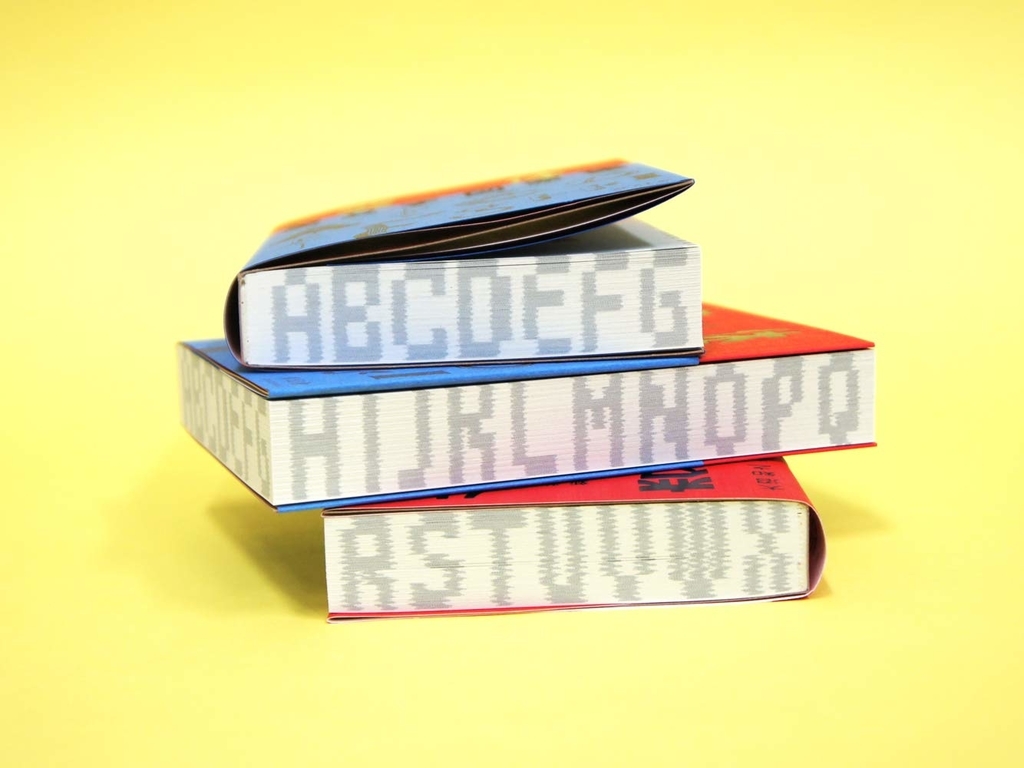
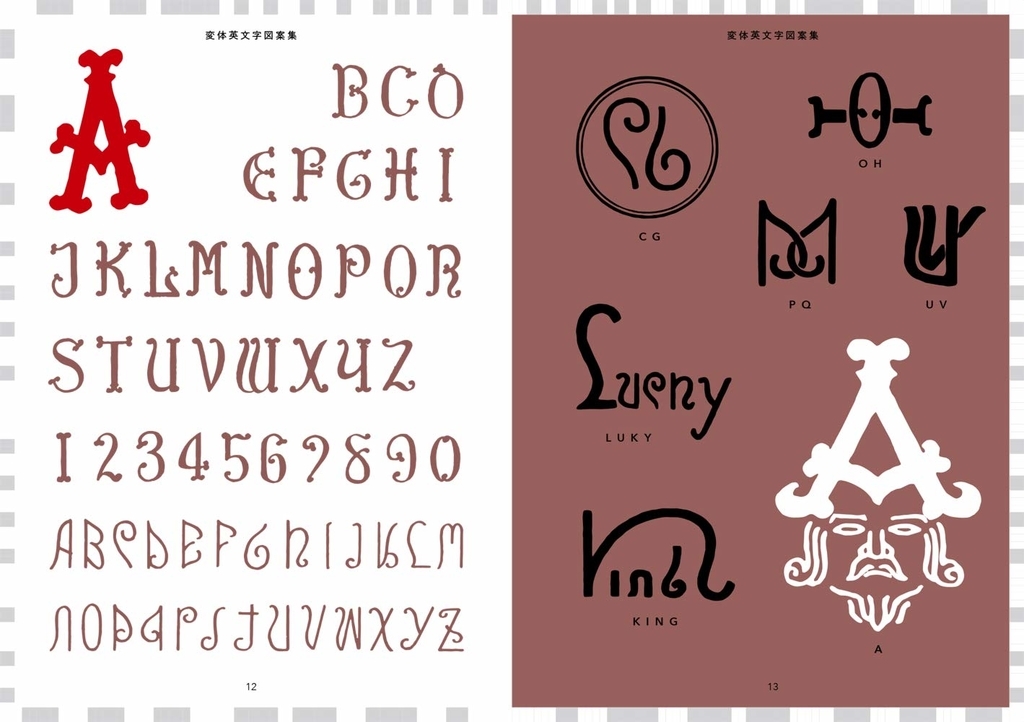
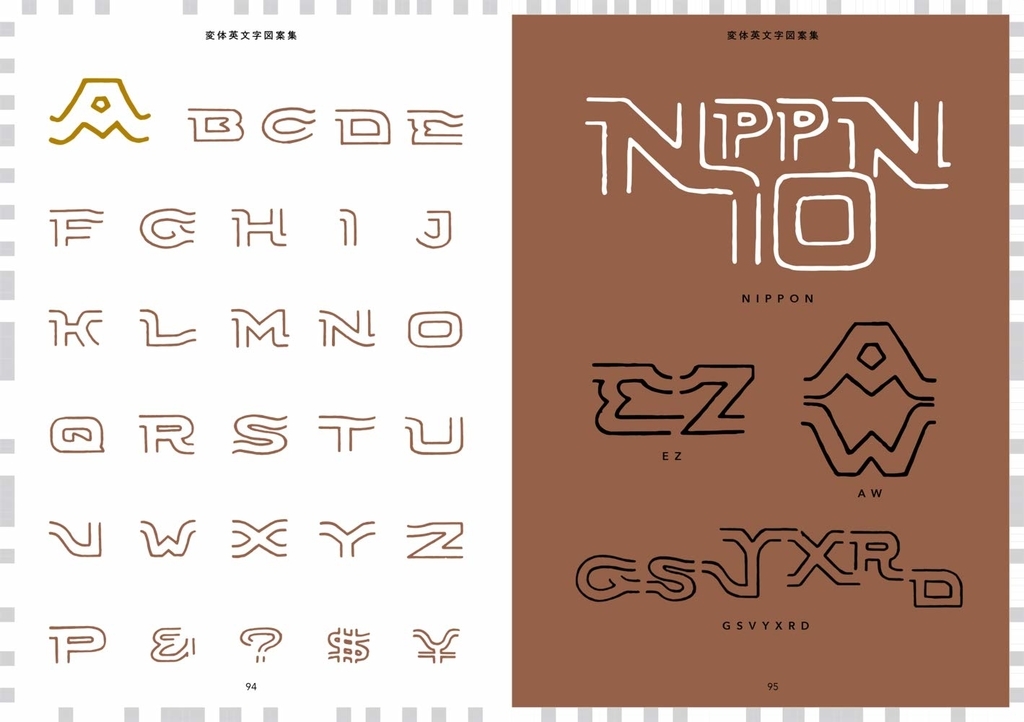
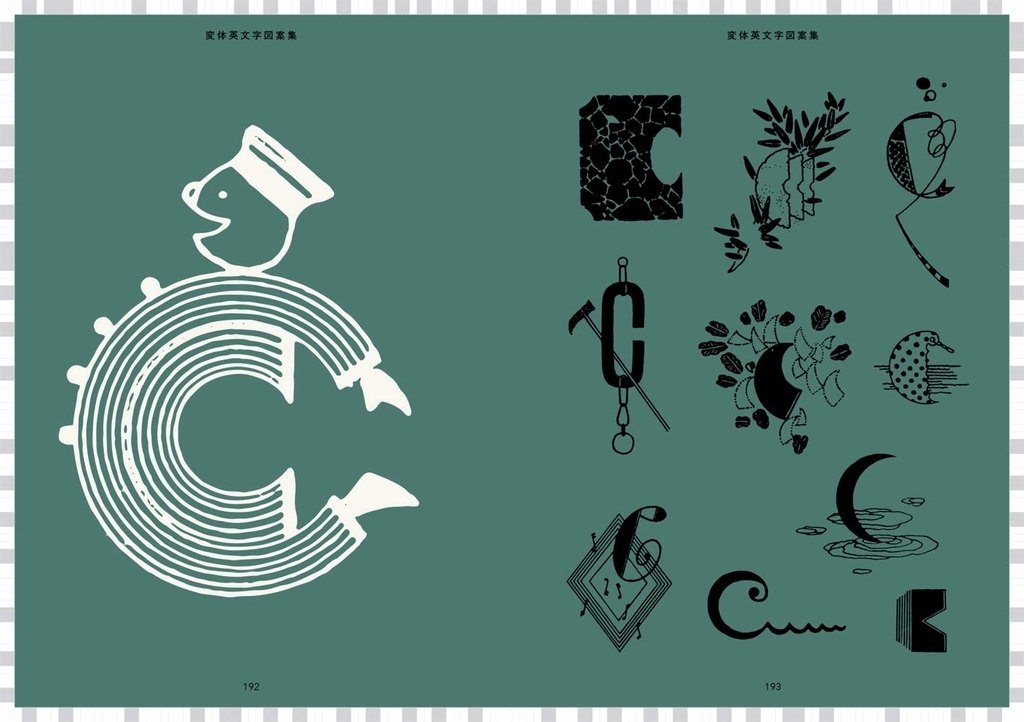
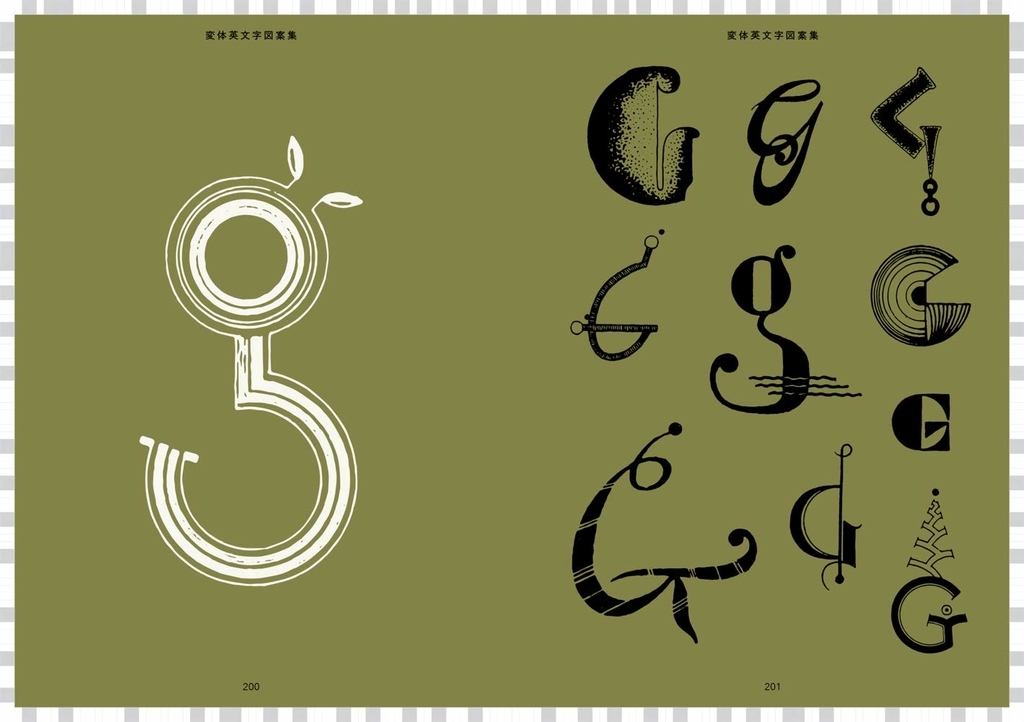
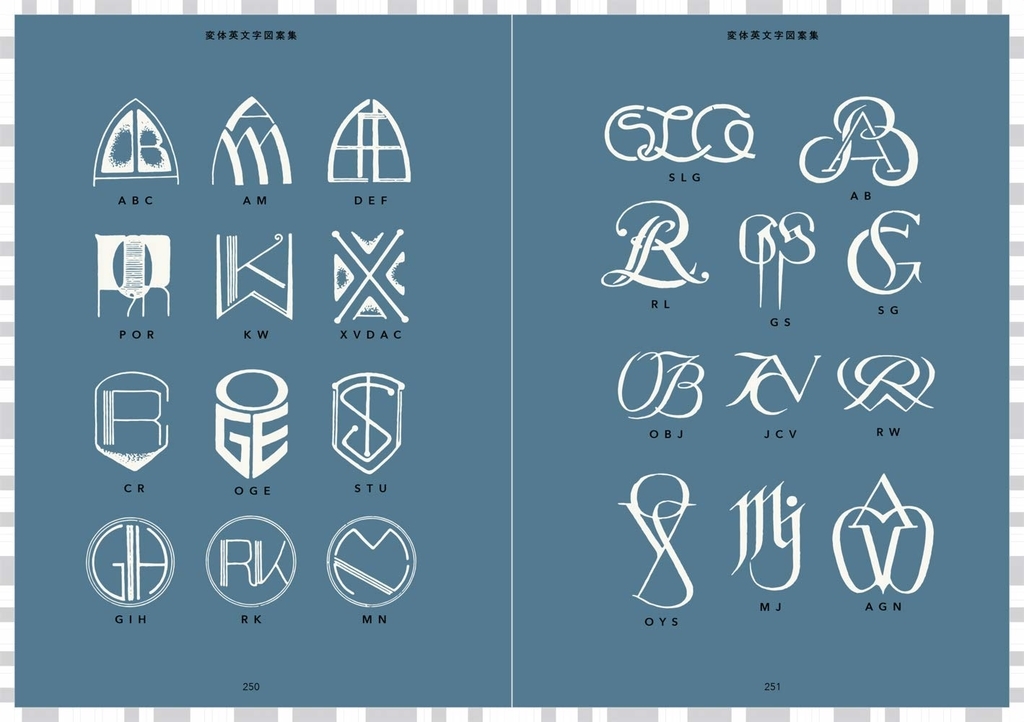
ビジュアル文庫 「描き文字図案集」復刻シリーズ 第3弾!
60年代、デザインの黎明期代に考案された楽しく、美しい英字の世界。
戦後の印刷物、掲示、看板などに書かれたアルファベットおよび英数字の実用的な字体をはじめ、装飾・美術的なさまざまなスタイルを第1章「英字スタイル」とし70パターン掲載。
これをもとに第2章「英字モノグラム」は、ABCと数字をあらゆる角度から組み合わせたモノグラムのバリエーションを約1,000種収録。
本書は、『変体英文字図案集』(1962年 佳生書房刊)を完全収録し再構成したものです。
序文 装丁家 平野甲賀
Title: Old-Style Alphabet Lettering of Japan
This volume is composed of a main section of alphabet and number fonts that were used for both practical and ornamental purposes, and a smaller section underneath on each page of monograms formed from combinations of alphabet letters and numbers in a variety of angles.
After World War II, there was a sharp increase in Japan of printed materials, notices, and guide boards and explanation boards written in foreign languages, particularly English, seen everywhere indoors and outdoors, so that foreign languages became a common feature of life for the Japanese.
The English letter styles and the marks that accompany them expressed in these various printed materials and are in bold and other types of fonts with well-defined strong form, delicate beauty, lightly rhythmical lines, and dignified formal arrangements appropriate for the main purposes of their texts, pictures, and designs.
If these objects were put on exhibit, how they would delight the eye and what quiet enjoyment they would give the heart!
辻克己Profile●1892~1982年。岸田劉生、萩原中、木村荘大等と武者小路実篤の率いる「新しき村」の発起人となって九州・日向での生活を始める。昭和八年から十一年にかけて「現代図案カット大集成」等七冊に及ぶ一連の図案集を手がける。終戦後、年二回程の個展、又所属していた大調和会に出品するなどの創作活動を続ける。
ビジュアル文庫「描き文字図案集」復刻シリーズ第2弾「実用手描文字 『実用図案文字と意匠』新装改訂復刻版」
書体やロゴ制作のアイデアの源にも!